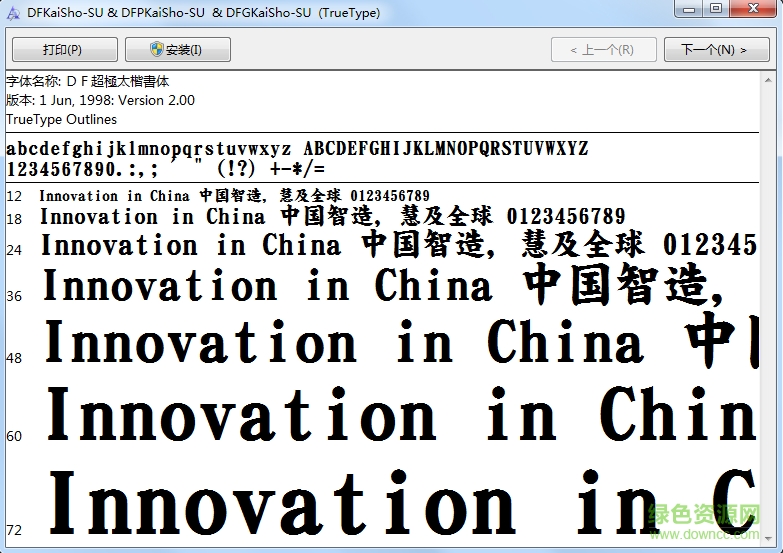
DF超極太楷書體Regular Version 2.20字體(字體家族名稱:DF超極太楷書體;字體風(fēng)格樣式名稱:Regular),共有7538個(gè)字符。
超極太楷書體以楷書為模板創(chuàng)作而成,擁有完整的字庫(kù),本字體安裝后顯示的名稱為DFKaiSho-SU、DFPKaiSho-SU、DFGKaiSho-SU三個(gè)名稱,請(qǐng)?jiān)诜斌w狀態(tài)下使用!